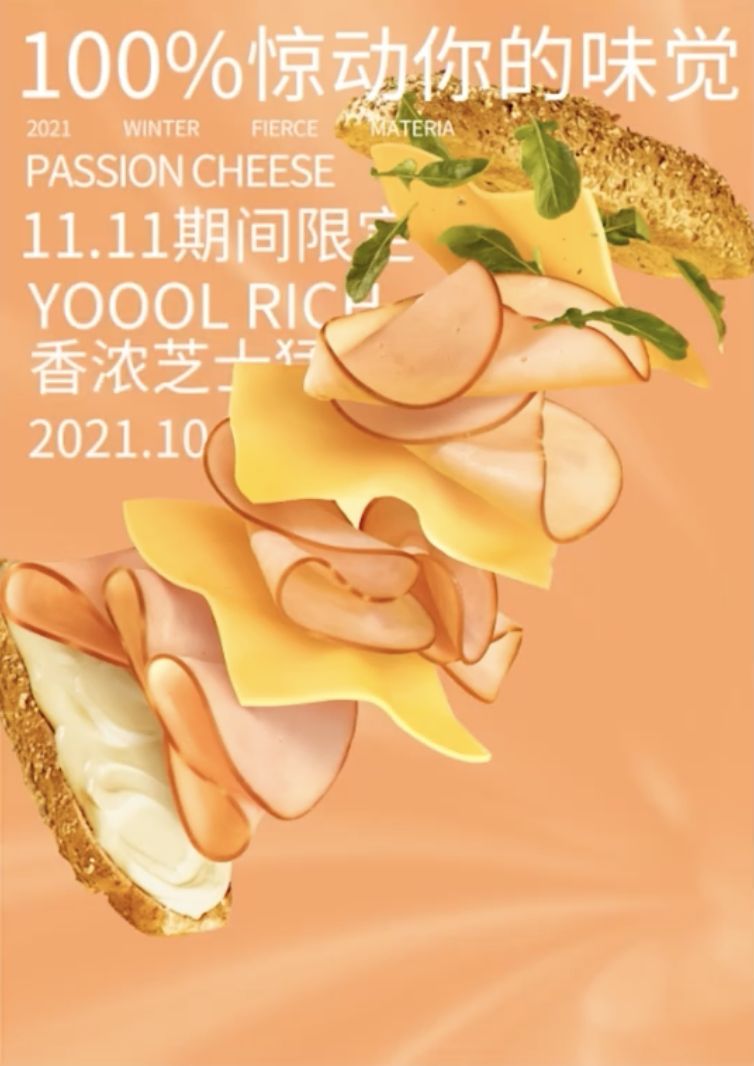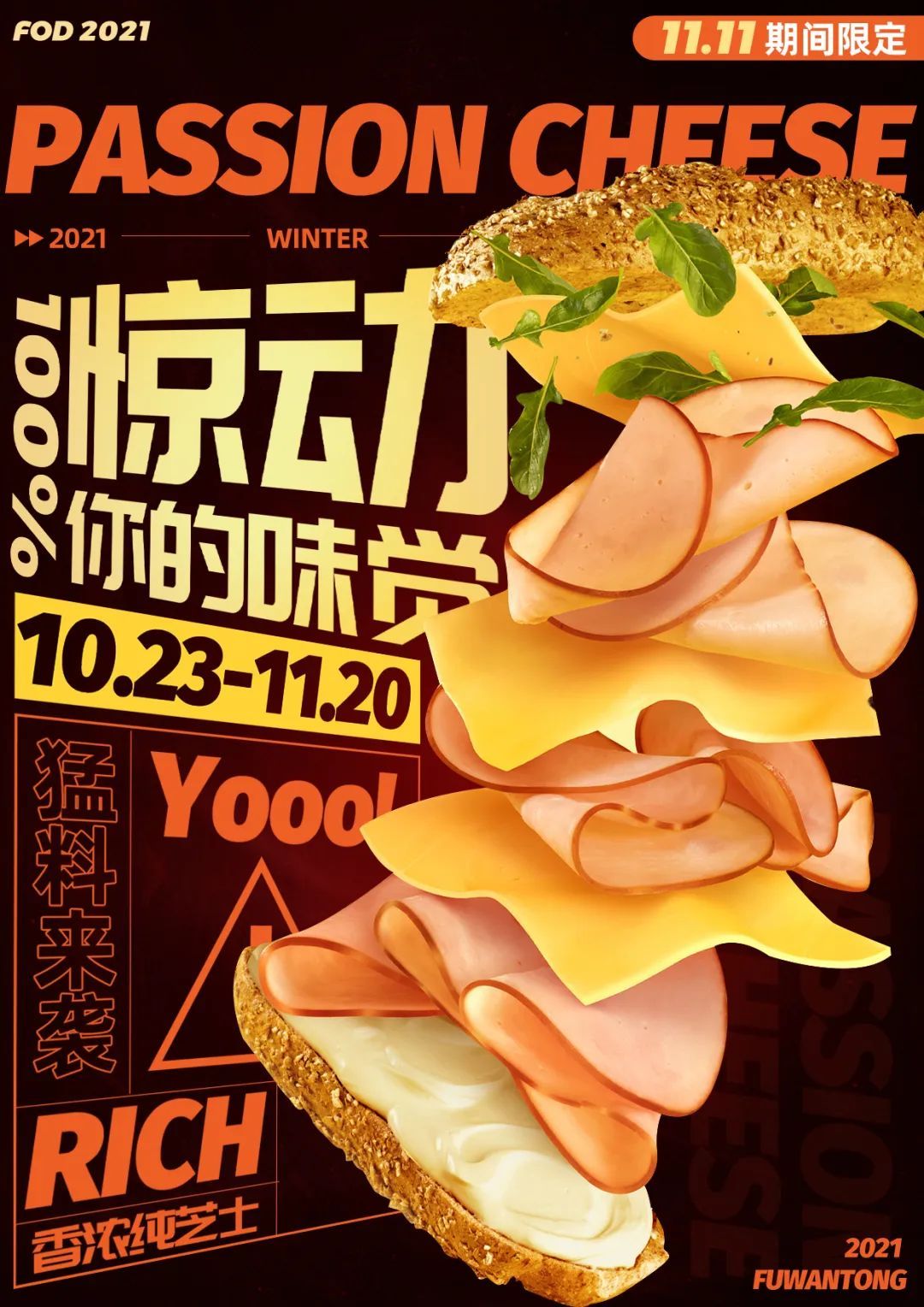
在做海报的时候,你会因为排版不好看而烦躁吗?
最近接到了一个粉丝的求助,说汉堡海报不会排版,来找我帮他指点;最后指导过的海报被甲方一稿过了,还夸他做出了“买不起”的样子,一起来看看改稿过程:
改版前
改版后
美食海报比较重要的一点就是突出美食,巧妙运用食物色彩组合,抓住宣传重点,来促成消费。
改版前的海报可以很明显地看出问题:重心集中在海边左上角,右下角大部分空白,整体版式有一种重心不稳的感觉;
而且左上角的文案信息,排版凌乱、还被主体图片遮挡了一部分,造成信息展示不全。
同时,在颜色的搭配上,海报背景色选择了和汉堡图片类似的同色,没有很明显的突出食物图片;
改版后的海报用的还是之前的素材图片,但是不论从版式、还是字体设计、色彩搭配上,都散发了一种美食的诱惑; 从版式上看,海报画面整体呈现出左右的分布趋势,主要的文案信息在左边,图片在右边,具有平衡、稳定、互相呼应的特点。 从文字设计上看,用自由变换工具将文字部分做了三个字体斜切设计,同时配合右边不规则的主体图片,产生了一种空间错位感,更加立体、生动; 从色彩搭配上看,改版后的海报背景选择了黑色系,能够很明显地突出主体图片,同时文案的颜色也用了黄色和红色系,在黑色的背景下更加明显和突出。
这个改版后的海报,我比较满意的就是文字斜切的处理,做出了一种空间变化的感觉。在平面设计中,一个好的文字设计也能增添不少的亮点。
平面海报设计是否出彩,版式、色彩、创意、字体等都非常重要,尤其是在商业平面设计中,要求图文信息简洁、清晰,并且通过合理的编排使版面具有强烈的艺术感染力和视觉冲击力,给人留下深刻的印象。